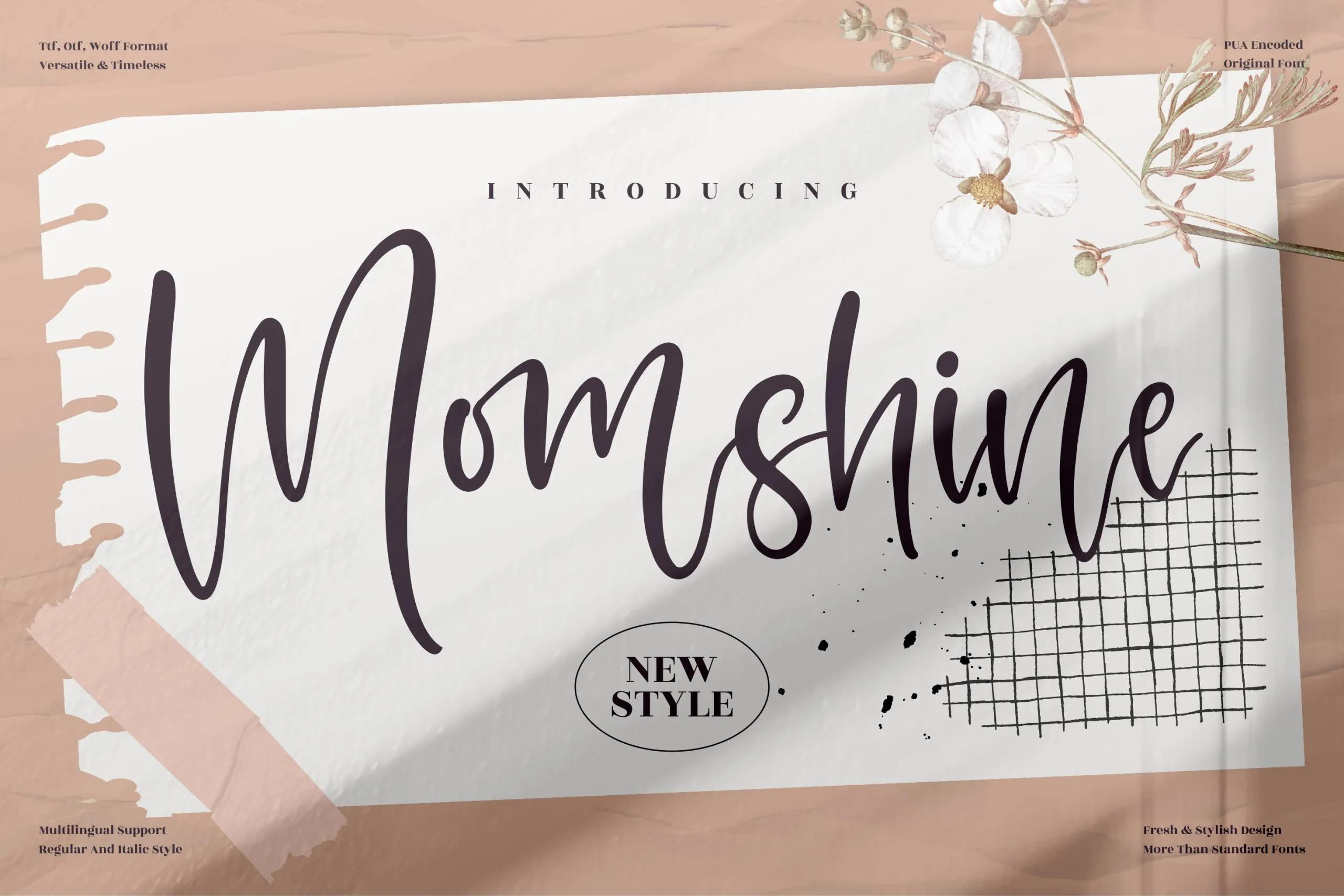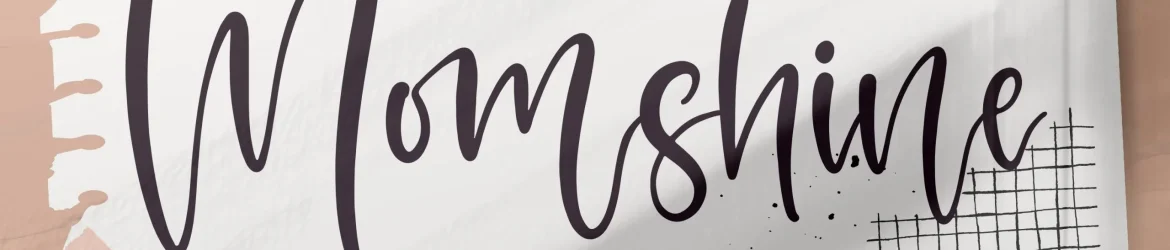
Aqui está uma versão em português para a descrição solicitada: Esta é uma fonte de calligrafia romântica perfeita para qualquer projeto, seja ele uma logo ou um design de embalagens de produto, desde as etiquetas até os cartões de convite e encomendas. Ideal para elementos como camisetas, mugs, selos, ilustrações em fotografias, marcas de imagem e eventos especiais. A fonte “Momshine” foi criada pelo designer perspectype, com uma abordagem que se destaca por suas linhas delicadas e graciosas. Suavemente fluida e cheia de vida, ela transmite um toque especial para qualquer projeto que precise de uma escrita agradável. A fonte é adequada para criações tanto artísticas quanto funcionais, como ilustrações em fotografias, selos, marcas de imagem e até mesmo o estilizado texto das camisetas e mugs. Não importa qual aplicação você escolha para essa elegante chamada, a “Momshine” certamente dará um toque único e romântico ao seu trabalho.